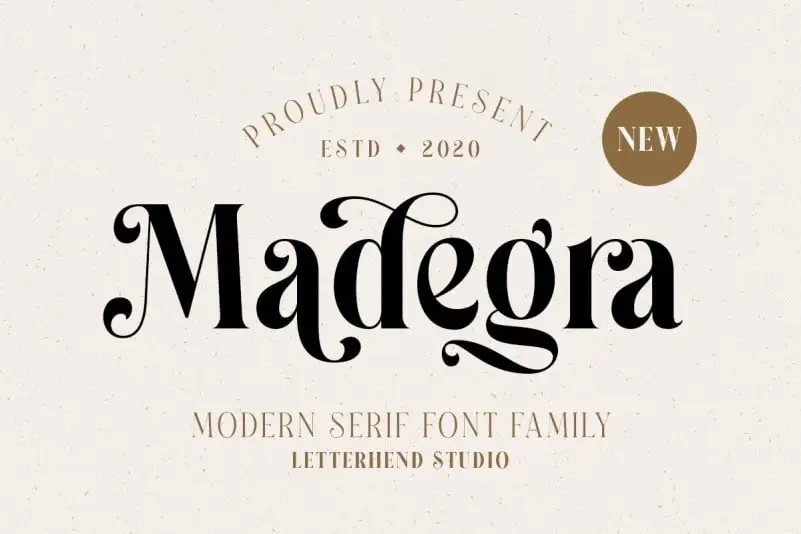
Madegra Serif Font – Download Grátis
A Madegra Serif é uma nova e única fonte serif que trouxe a Letterhend Studio ao mundo do design tipoográfico. Este tipo de letra apresenta alternativas com swashes, elementos que adicionam um toque interessante à escrita ou logotipo. A linha clara e organizada das serifas é complementada pela ótima forma dos swashes, criando uma fonte ainda mais única. O que torna a Madegra Serif ainda mais especial são seus 9 estilos de peso diferentes, que permitem escolher o melhor para suas necessidades específicas. Este tipo de letra, tanto para escritas quanto para logotipos, oferece um equilíbrio elegante e sofisticado, ideal para qualquer projeto visual. Se você está procurando uma fonte diferenciada capaz de destacar seu design em um mundo cada vez mais competitivo, a Madegra Serif pode ser sua escolha perfeita.